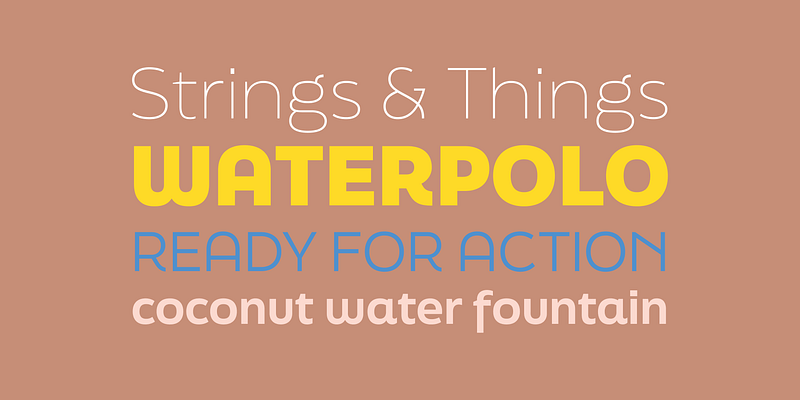
FinalSix ist die typografische Adaption eines eigens für das Finale der Wasserball-Europameisterschaften 2014 gestalteten Schriftzugs. Während der Arbeit an den Grafiken für diese Veranstaltung hatte José Manuel Urós die Idee, einen Zeichensatz zu erstellen, der die Idee der wellenförmigen Bewegung von Wasser in einem Pool widerspiegelt. Mit dem Wort „WATERPOLO“ als visuelle Referenz haben die Zeichen von FinalSix abgerundete Ober- und Unterseiten und Diagonalen, wodurch ein welliges Gefühl entsteht. Urós definiert den Prozess als „form follows meaning“ (die Form folgt der Bedeutung). Um die Persönlichkeit dieser Schrift so weit wie möglich zu bewahren, befinden sich im Standardzeichensatz die eigenwilligsten Zeichen, während die schlichteren Variationen für die Editorial-Schrift in einem stilistischen Zeichensatz zu finden sind.